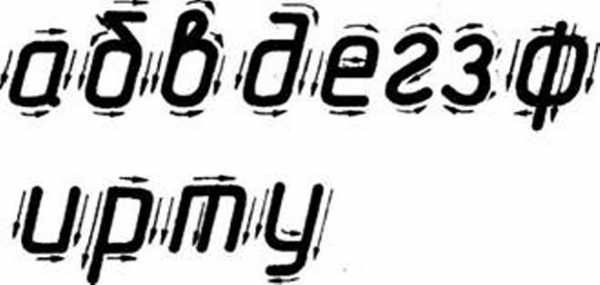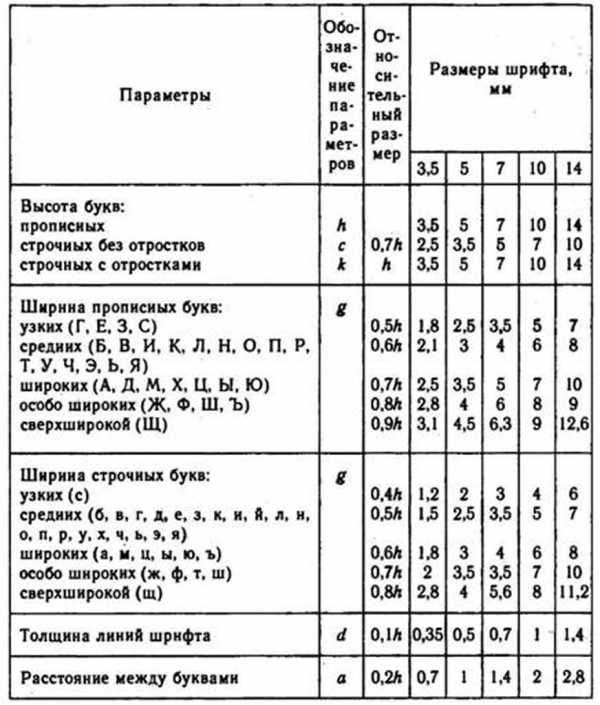
Шрифты чертежные
Шрифты чертежные (тип А) Правила написания букв и цифр определяются ГОСТ 2.304-81. Рекомендуется вначале выполнить упражнения по написанию шрифта всего алфавита на отдельном листе, используя вспомогательную сетку (рис.3), для того чтобы выработать глазомер для правильного соотношения размеров и наклона (75° ) букв и цифр (75° ).После упражнений выполнить надписи на формате А4 (рис.4 и прил.8) уже без сетки, от руки, в глазомерном масштабе, соблюдая наклон букв, толщину линий шрифта и соотношения элементов шрифта по ГОСТ.
Рис. 3 |
Рис. 4 |
Все прописные, строчные буквы и цифры на листе имеют одну толщину (S) линий шрифта. Расстояние между буквами в слове равно 1,5 – 2S, между словами в предложении – 6S.
Наиболее характерные ошибки, на которые всегда обращают внимание: – не выдержаны размеры (высота) шрифта по ГОСТ; – буквы в строке “прыгают”; – не соблюдается горизонтальная линия; – наклон не у всех букв одинаков и т.д.
Рекомендации. Для того чтобы буквы не прыгали, соблюдалась их высота и предложения были горизонтальными, необходимо с помощью циркуля (кронциркуля с двумя иголками) или какого-либо другого приспособления продавить две параллельные линии по высоте строчных букв, в диапазоне которых выполнить начертание букв.
Основные теоретические положения по теме “Шрифты чертежные” гост 2.304-81
Размер соответствует номеру шрифта h и определяется высотой прописных букв в мм. ГОСТ допускает следующие номера (высоту прописных букв) шрифта:
2,5; 3,5; 5; 7; 10; 14; 20; 28; 40
Высота строчных букв на один размер меньше размера прописного шрифта. Например, для 10 шрифта высота прописной буквы 10 мм, а высота строчных букв будет 7 мм. Имеется зависимость ширины букв от их высоты:
Ширина прописных букв Г, Е, З, С – 6/14 h ; букв А,Д,Х Ц,Ы,Ю – 8/14 h; для букв Ж,М,Ъ – 9/14 h; Щ – 10/14 h; Ф – 11/14 h; для всех остальных – 7/14 h.
Ширина строчных букв з, с – 5/14 h ; букв а, м, ц, ъ, ы, ю – 7/14 h; ж – 8/14 h; т, ф, ш – 9/14 h; для всех остальных – 7/14 h.
ГОСТ устанавливает шрифт с наклоном (около 75° ) и без наклона, шрифт типа А и шрифт типа Б. Более распространенными являются шрифты наклонные типа А
| Стиль | рублёный, пропорциональный, минималистичный |
| Классификация | технический |
| Использование | в чертежах |
| Набор символов | русский, латинский, греческий алфавиты, технические символы |
Чертёжный шрифт — рукописный и компьютерный шрифт, который применяется для оформления чертежей и других технических документов. Шрифт стандартизован, его описывает международный стандарт ISO 3098 и такие национальные стандарты, как ГОСТ 2.304-81 и DIN 6776-1. Надписи чертёжным шрифтом могут выполняются от руки с использованием прямоугольной или наклонной сетки, могут использоваться трафареты и сухой перенос, а также компьютерный набор.
Рис. 39. Учет межбуквенного просвета при написании слов: а — правильно; б — неправильно
Рис. 40. Цифры и знаки
Начертание цифр и знаков показано на рисунке 40. (При выполнении чертежей выбирайте высоту шрифта не менее 3,5 мм.)